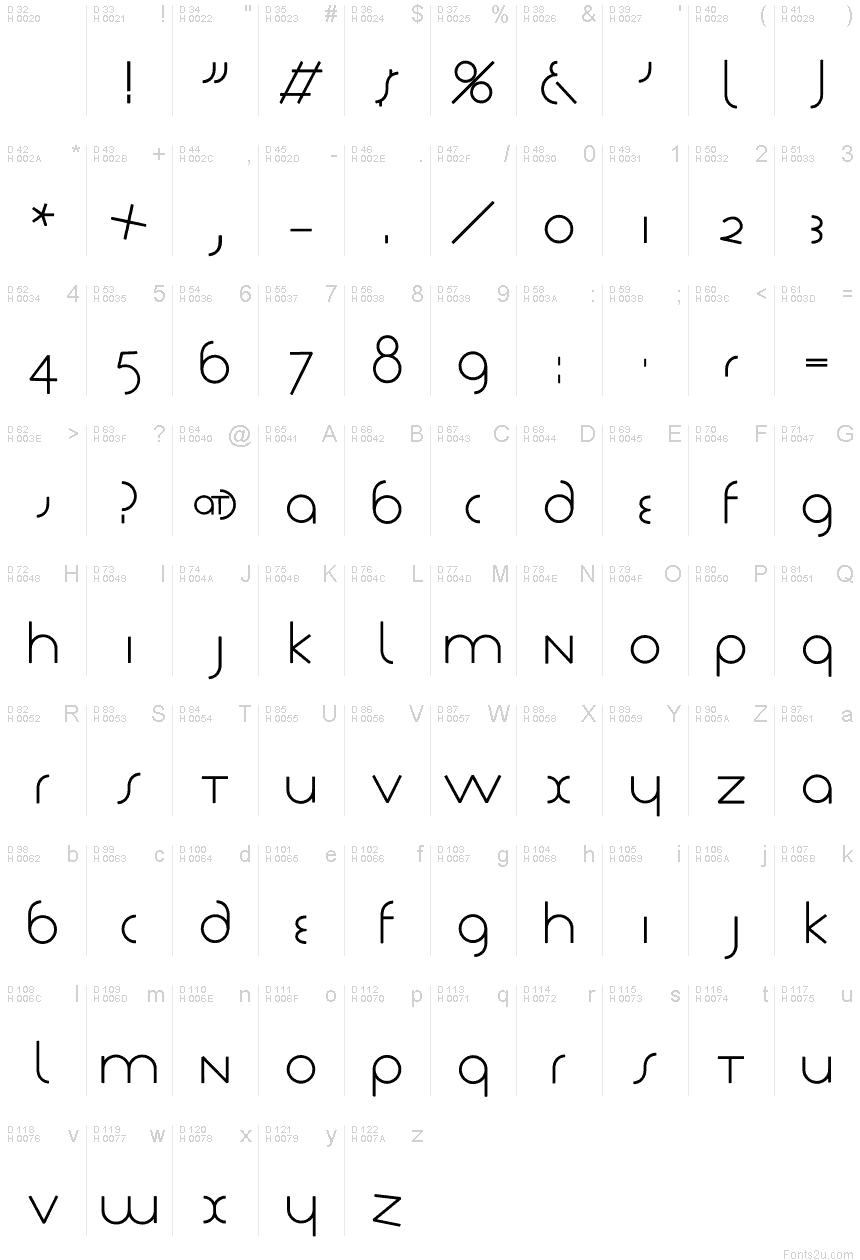
Tschich, zaprojektowane przez M. Klein - Fonteria, to darmowy geometryczny krój pisma ekspozycyjnego o smukłych, jednoliniowych pociągnięciach i niezwykle oszczędnej sylwece. Jego zaokrąglone łuki, szerokie krzywe i ścięte poziome kreski nadają literom wyrazisty, nowoczesny profil z subtelną geometrią inspirowaną Bauhausem.
Opakowania stanowią dobre otoczenie dla tych czystych, skonstruowanych form, zwłaszcza w przypadku kosmetyków, artykułów piśmiennych i artykułów gospodarstwa domowego o zacięciu designerskim. Nadaje się również na plakaty wystawowe, jednak jej najbardziej przekonującą rolą jest powściągliwy logotyp dla współczesnego studia lub marki produktów.